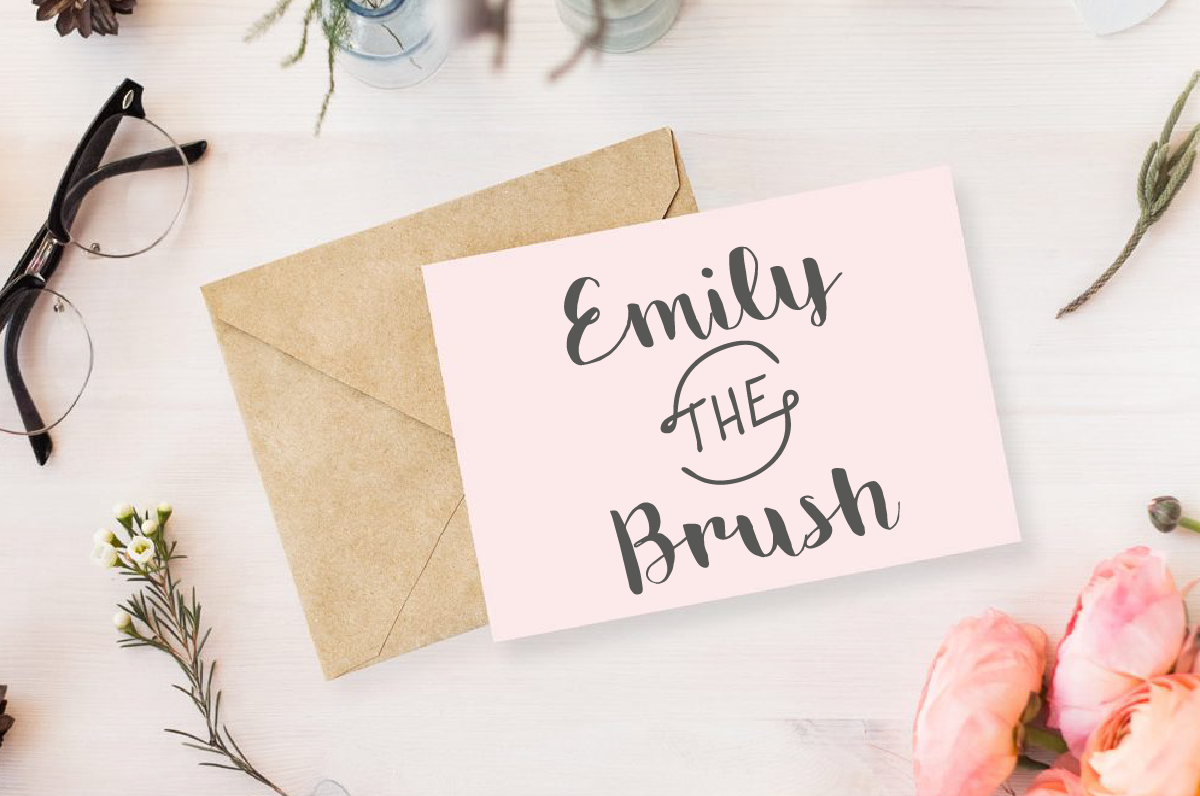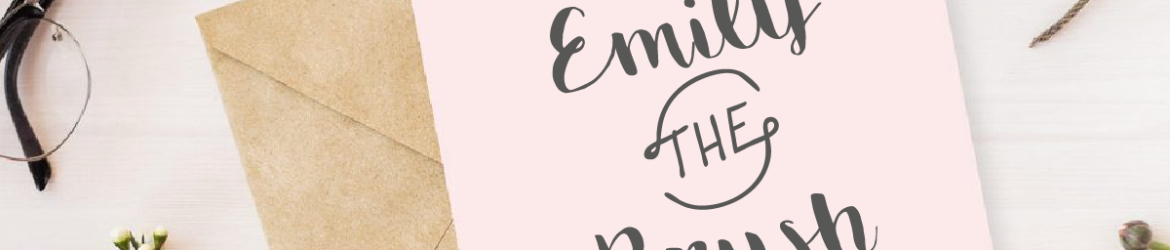
Emily The Brush Font – Download Grátis
A Emily The Brush é uma fonte Brush Handwriting Display criada pela paixão inabalável dos designers por Letraria e Fontes Feitas à Mão. Inspirada nas tradições do xilográfico, essa fonte oferece um toque informal graças às formas originais que adicionou. A coleção de caracteres inclui dois conjuntos de Glyphs Alternativos, acessíveis via teclado através da função OpenType, simplesmente ative a opção “Alternativo” de seu software e siga as instruções fornecidas. Através da mão do designer, o Talens Brush Pen 700 foi usado para desenhar essas formas não convencionais, tornando Emily The Brush perfeitamente adequada para aplicativos como anúncios, cartazes e cartões de agradecimento. Com seu estilo único e original, esta fonte é uma opção única para quem busca criar identidades gráficas ou designs digitais que destaquem sua personalidade e criatividade.